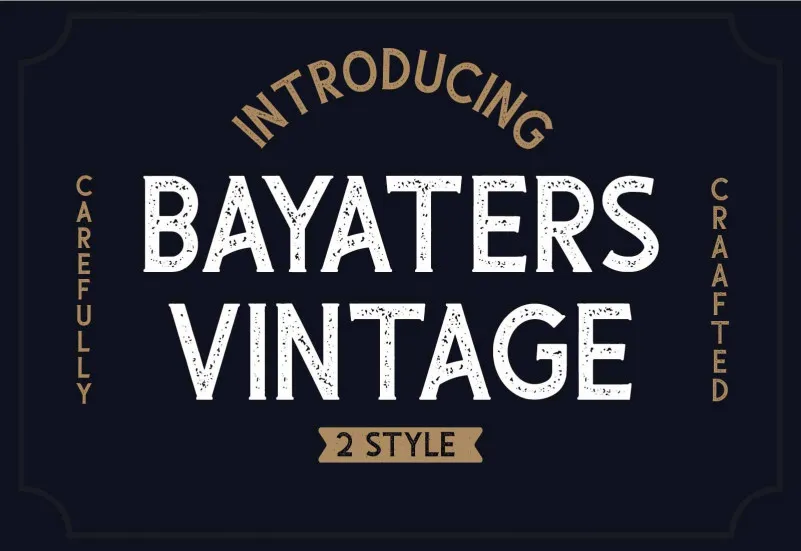
A Bayaters Font é uma opção imbatível para qualquer designer que procura algo único e divertido no seu próximo projeto visual. Desenvolvida por Galatamen, esta fonte de exibição se destaca pela sua estética clássica e simples, mas também apresenta um impacto visual forte que certamente fará seu trabalho de transformar qualquer obra em algo ainda mais atraente. Com uma linha elegante e com uma aparência de simplicidade, Bayaters pode não parecer ser o tipo de fonte que se destaca, mas é sua capacidade de criar um efeito visível marcante que a torna realmente especial. Quando incorporada em qualquer projeto, seja ele em design gráfico, marketing digital ou até mesmo em impressões de alta qualidade, a Bayaters irá chamar a atenção dos usuários e transformar seu trabalho em algo único e memorável.